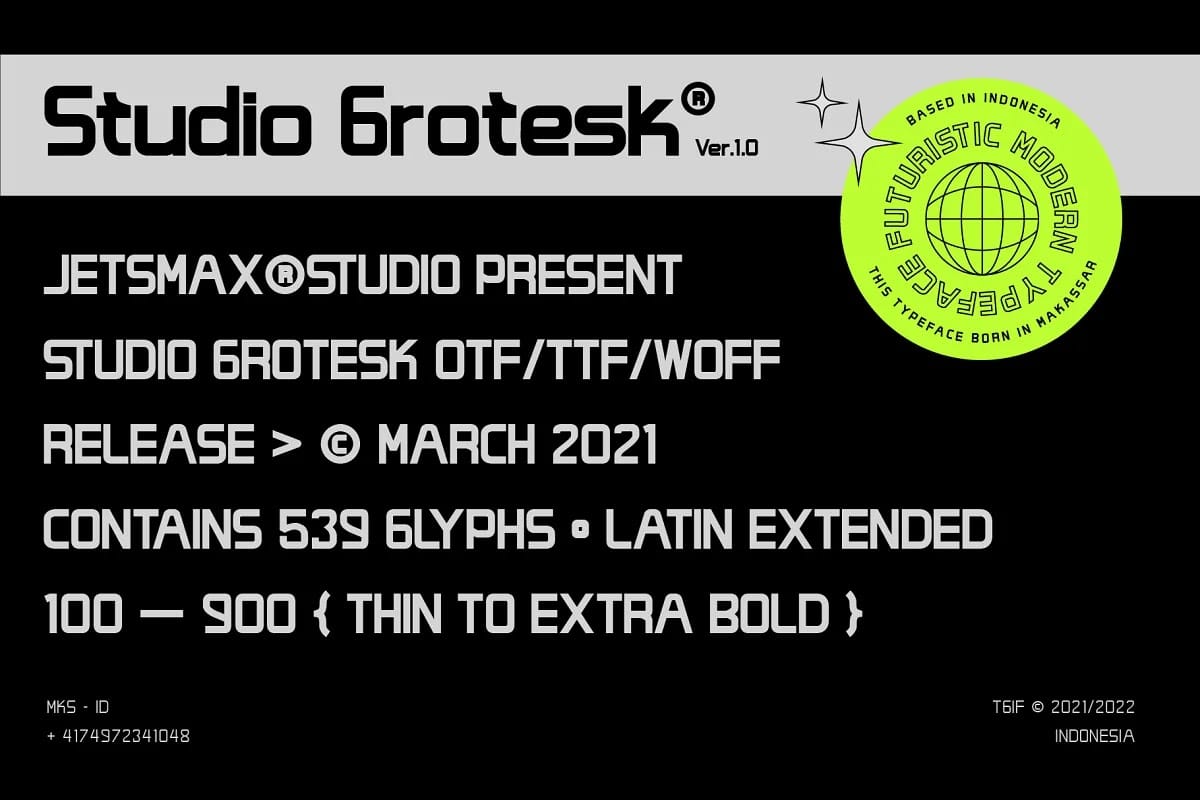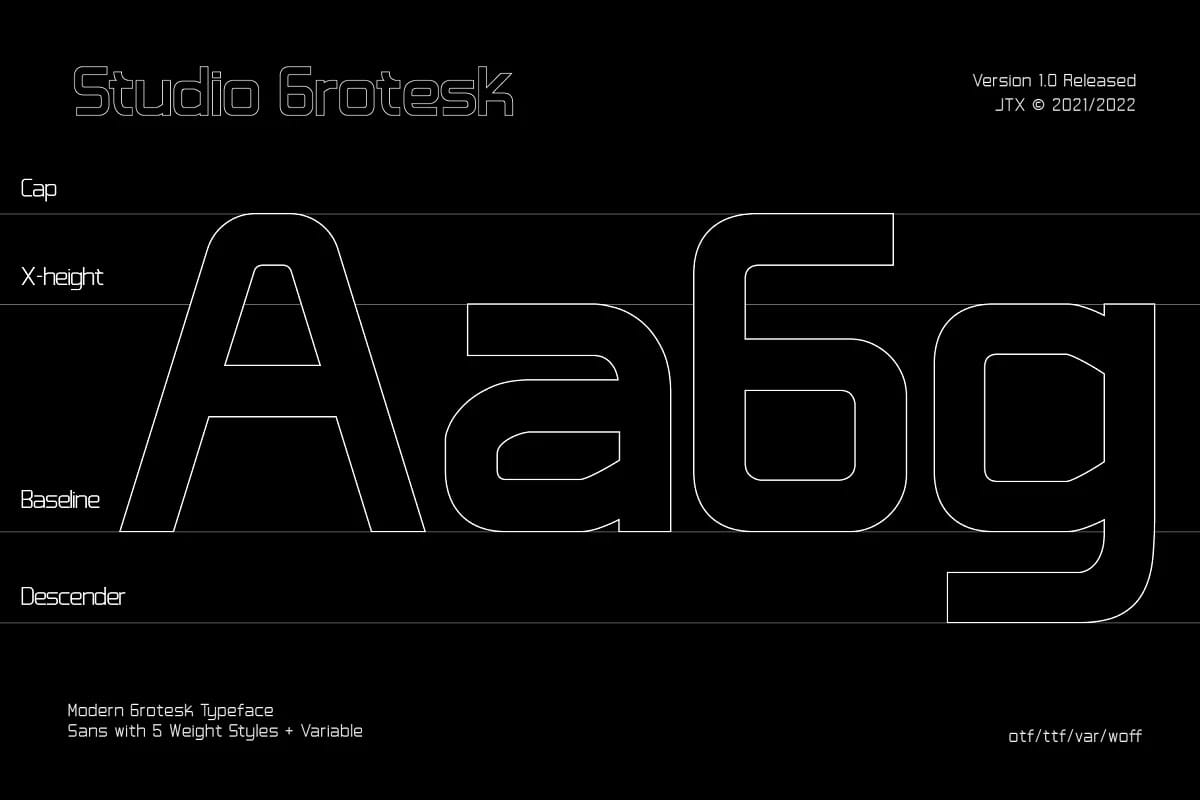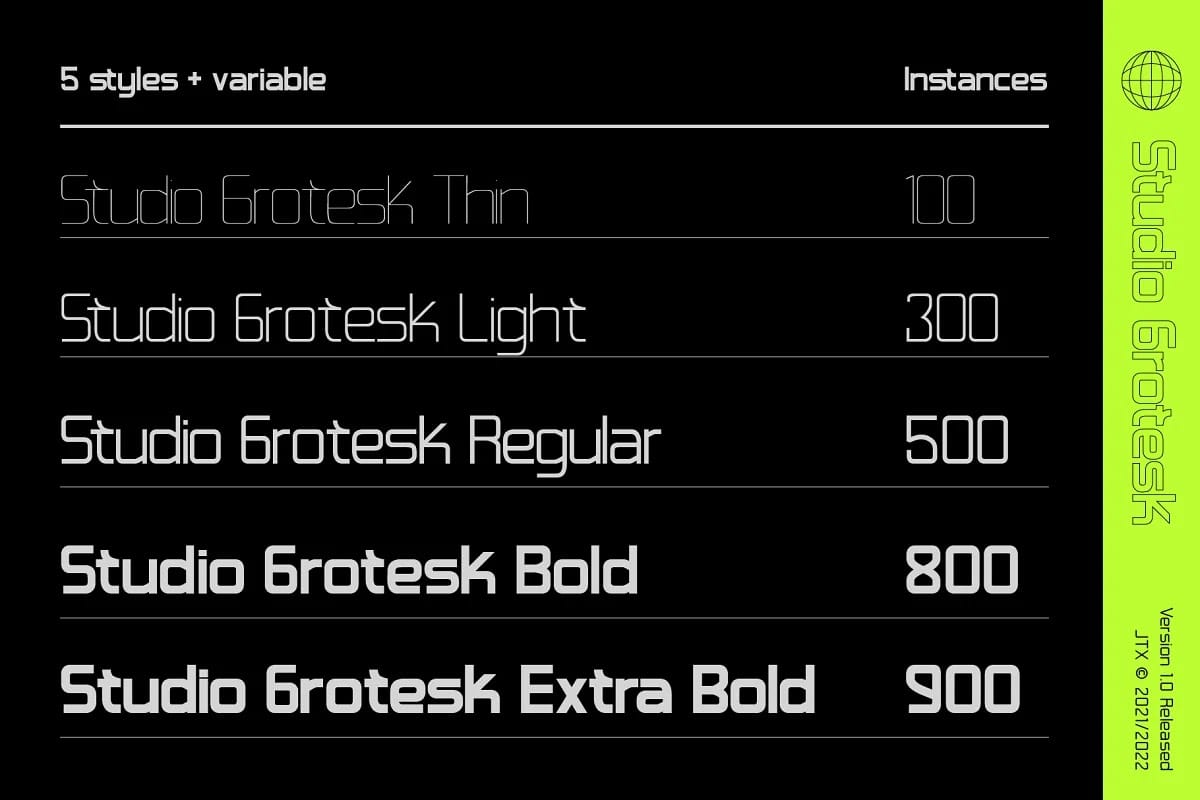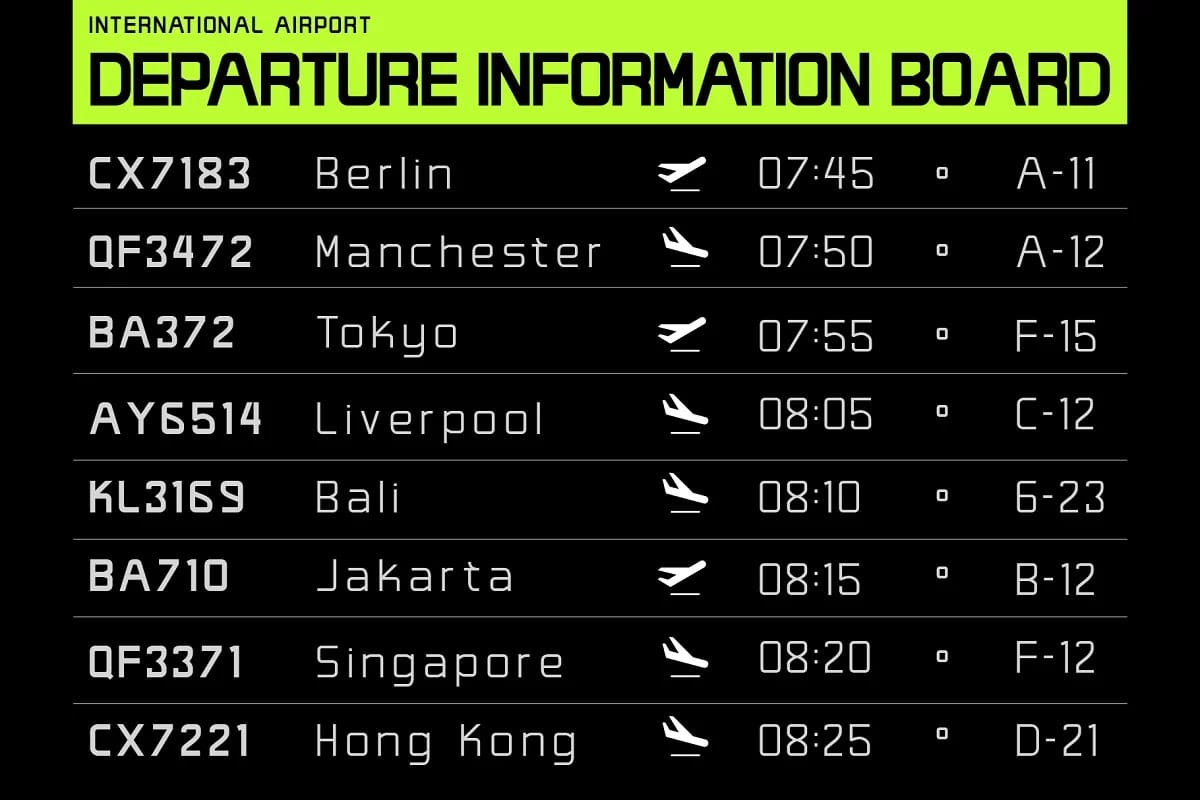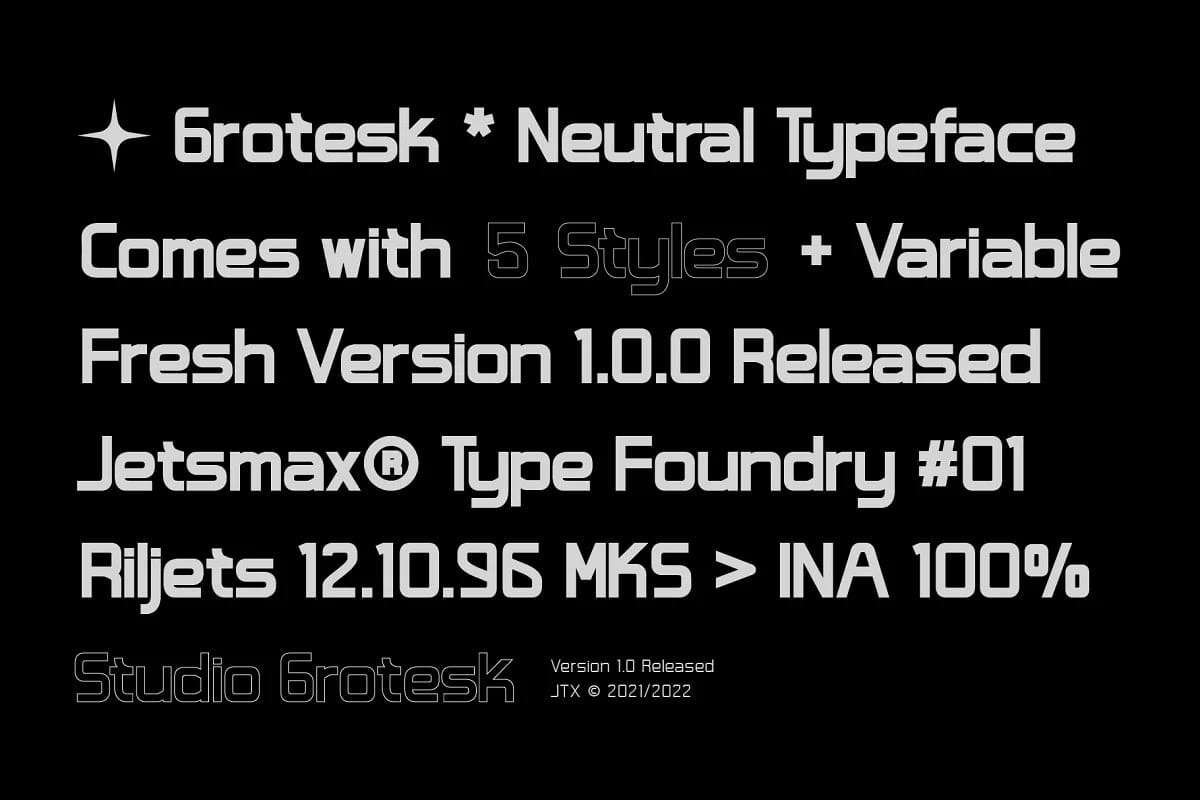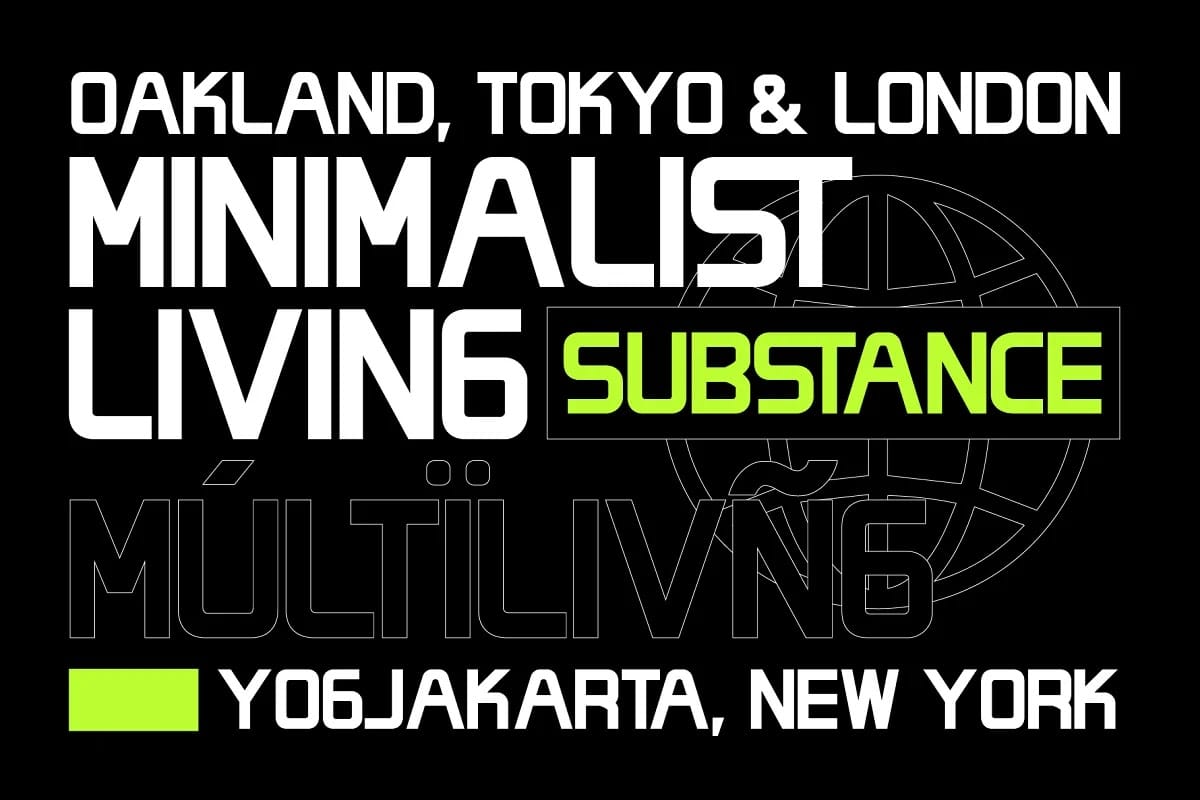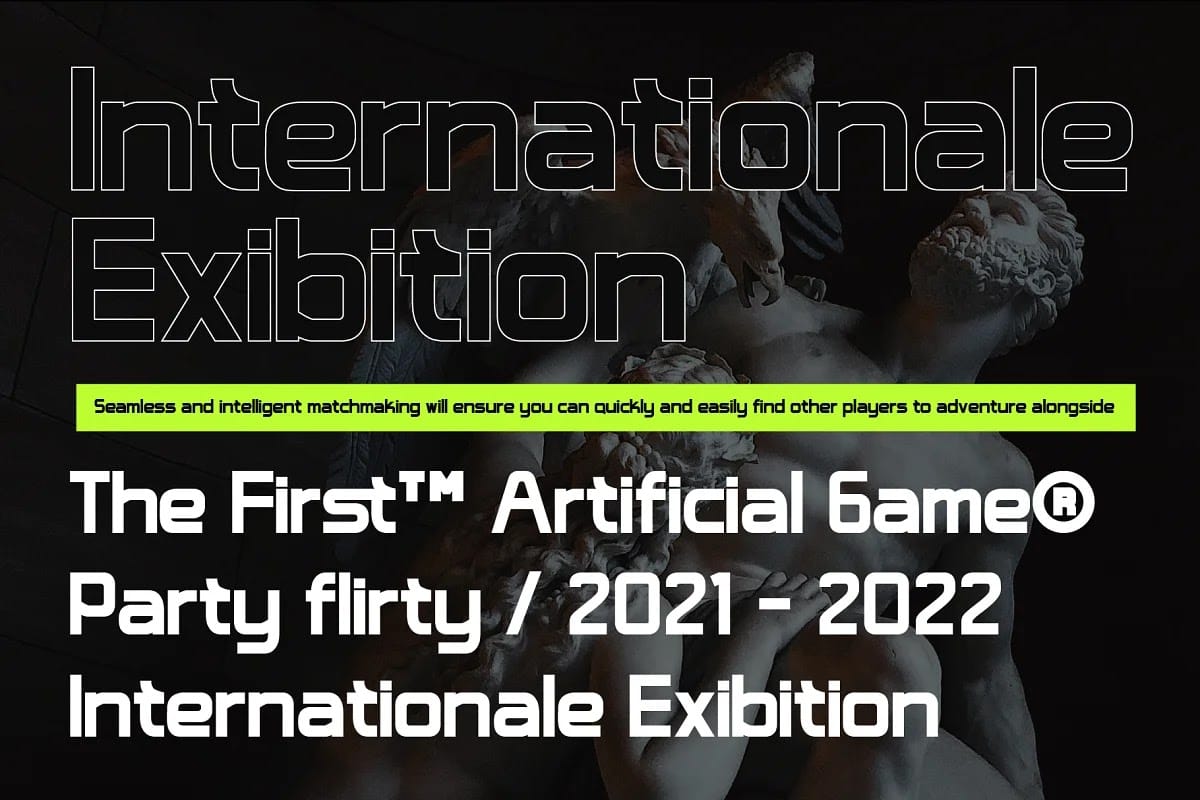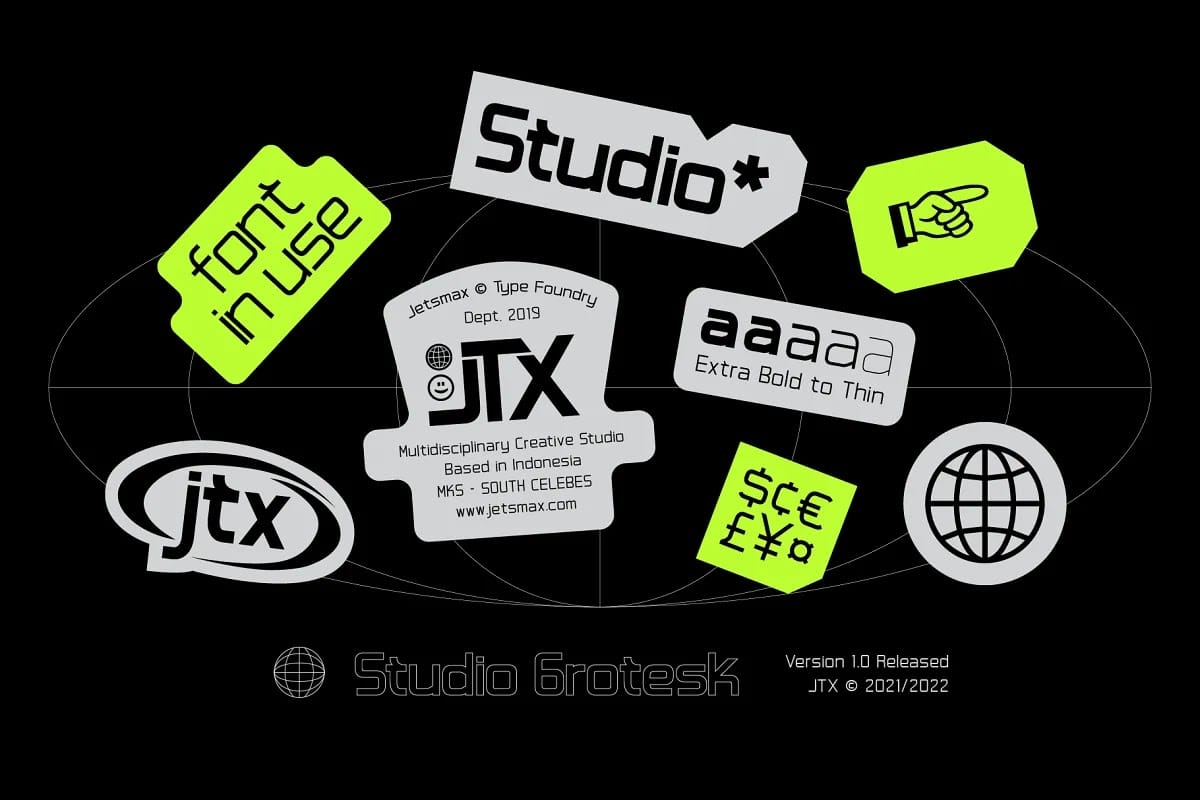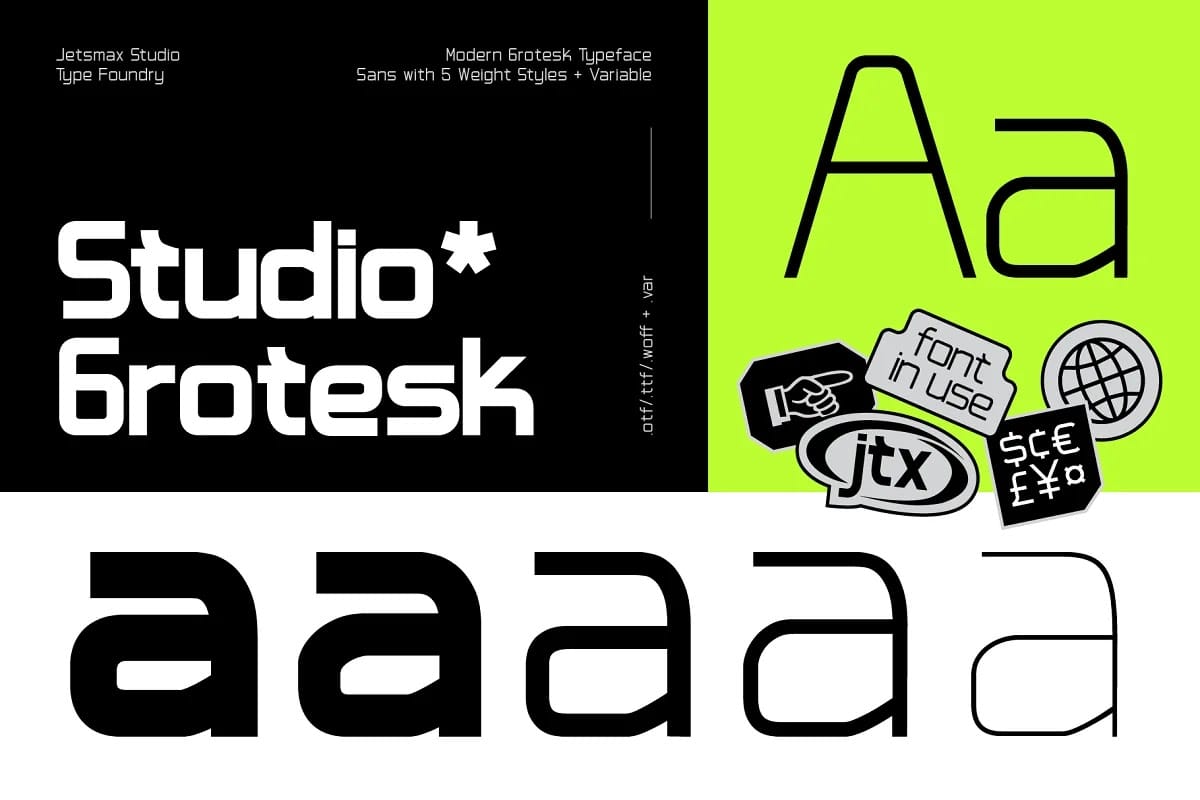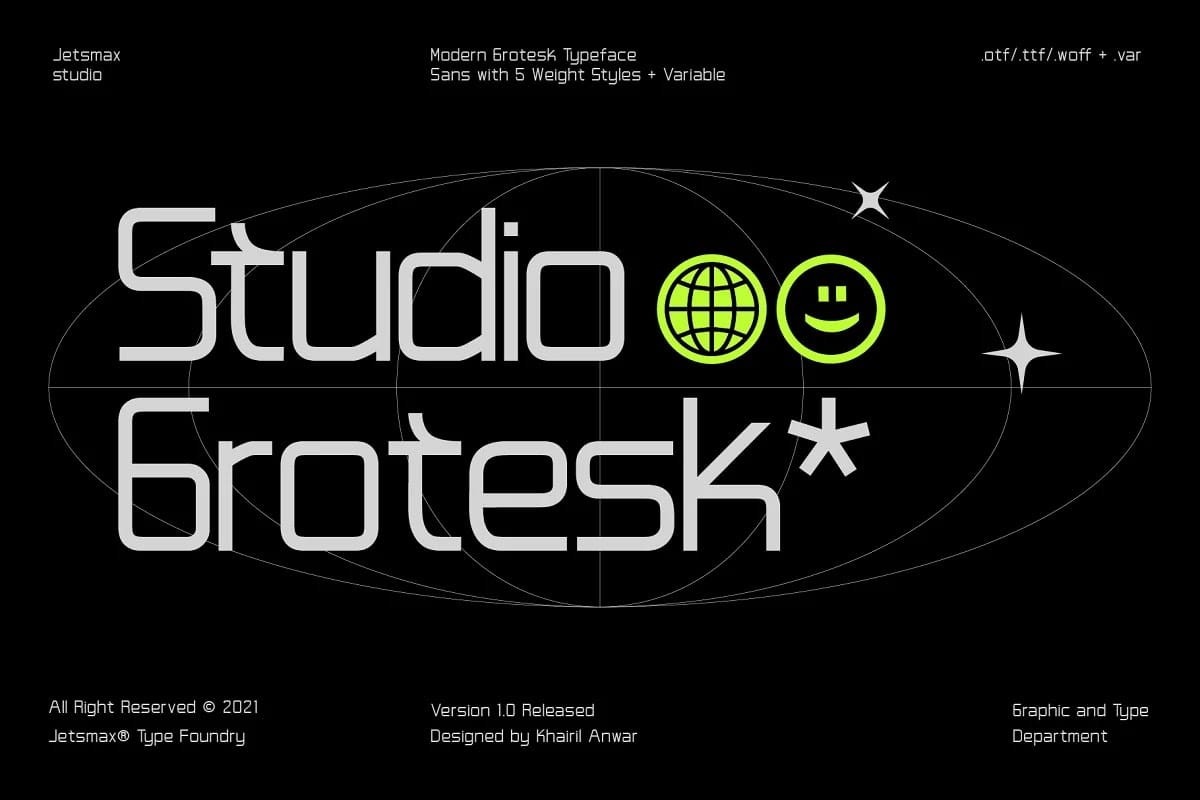
Studio Grotesk là kiểu chữ sans hiện đại với các đường nét thiết kế ấn tượng. Kiểu chữ đa dạng này sẽ thu hút sự chú ý của người đọc với thiết kế thời trang và gọn gàng. Với hơn 500 Glyphs, năm kiểu dáng và nhiều loại weight.